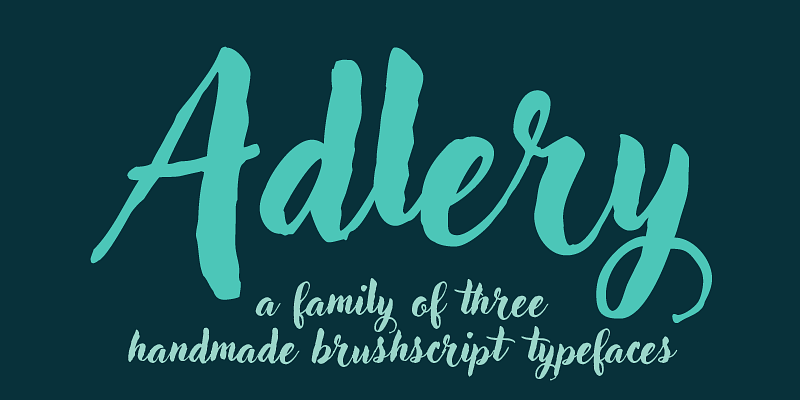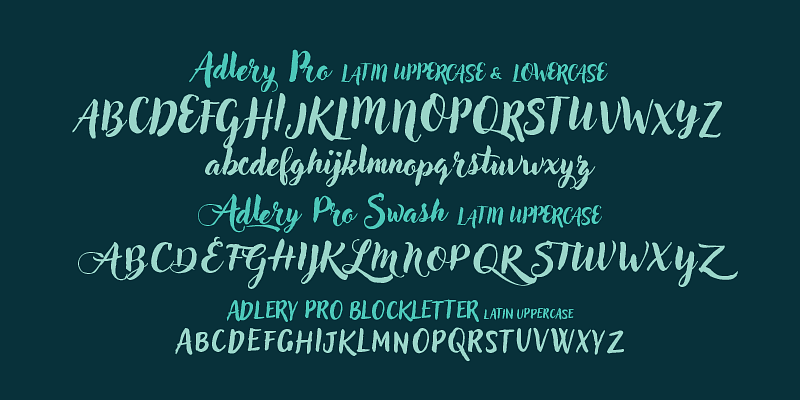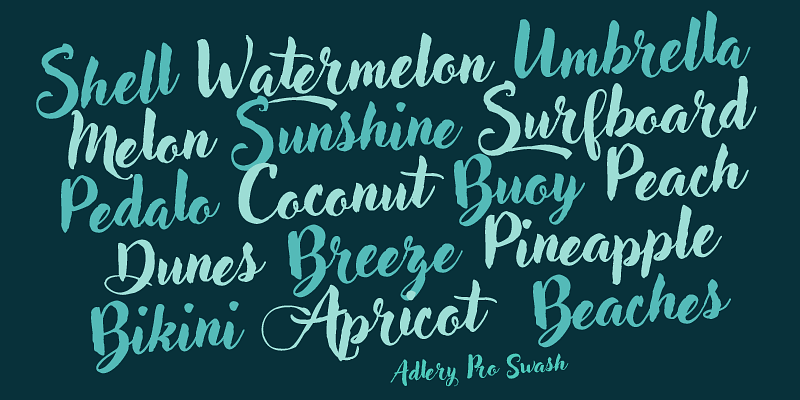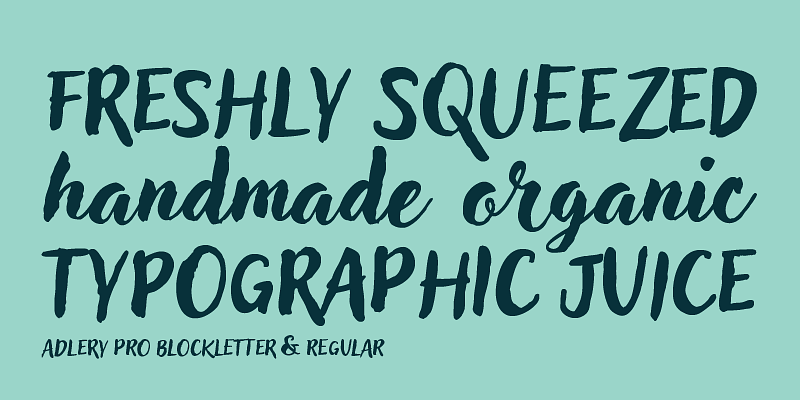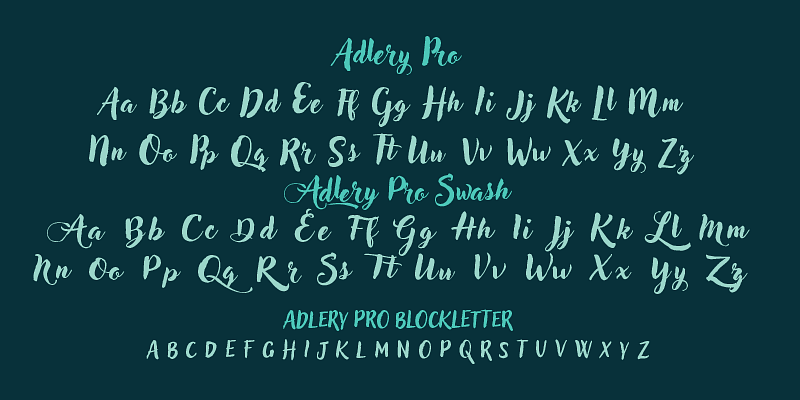
Adlery는 Cosimo Lorenzo Pancini가 전시용으로 디자인한 브러시 서체입니다. 필기체 느낌으로 중간 크기에서 가독성을 극대화하였습니다. 이 서체는 Basic, Swash 및 Blockletter Uppercase의 세 가지 스타일로 제공되며 이중 알파벳 소문자 세트가 번갈아 가며 작성되어 동일한 이중 문자가 없습니다.